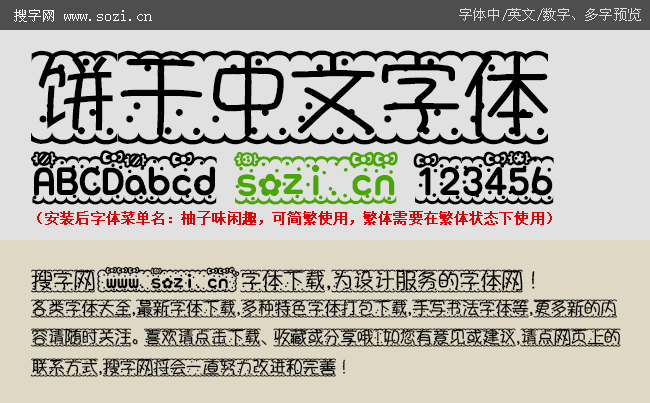
餅干中文字體
搜字網(wǎng)給大家提供一款很有趣的手機(jī)中文字體下載。字體名字叫餅干中文字體,這款手機(jī)字體是在POP字體的外面加上了卡通邊框圖案。該字體字里行間充滿童真稚趣,彰顯活潑靈動(dòng)的個(gè)性。特別適合喜歡手機(jī)字體個(gè)性一些的朋友在手機(jī)上安裝使用。